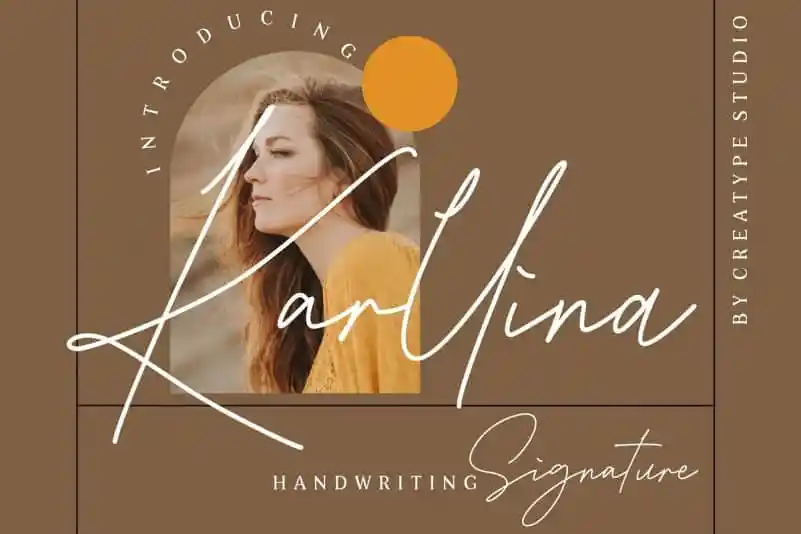
Karllina Handwritten Font
A Karllina Handwritten Font é uma elegante tipografia monoline que foi criada pela Creatype Studio com um estilo de escrita a mão. Este tipo de letra traz para os projetos digitais uma sensação de naturalidade, tornando-a perfeita para diversas aplicações. Suas linhas delicadas e texturas naturais a tornam ideal para projetos de marca, logotipos, desenhos de casamentos, posts nas redes sociais, anúncios, embalagens de produtos, designs dos produtos, etiquetas, fotografia, marcas d’água, convites, materiais de escritório e qualquer outro tipo de projeto que exija a delicadeza da arte à mão. Composta por uma estética sóbria e charmosa, a Karllina Handwritten Font é certamente um recurso visual indispensável para designers em busca de dar vida aos seus projetos.